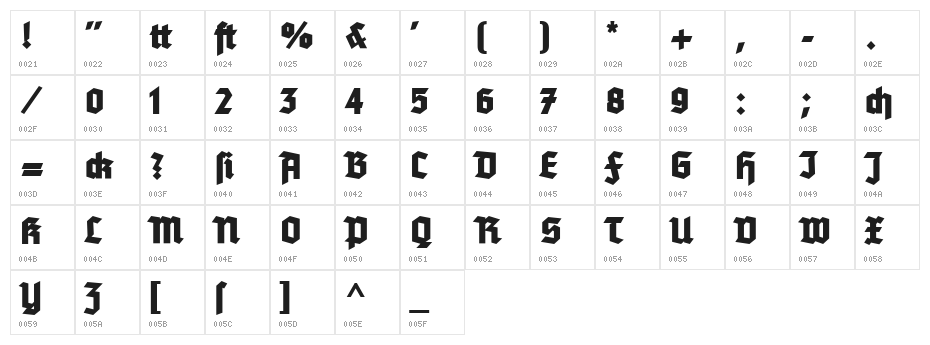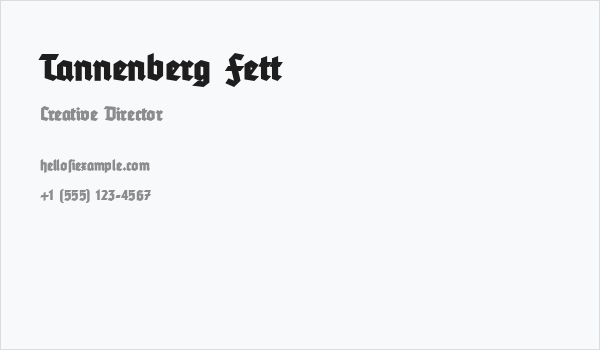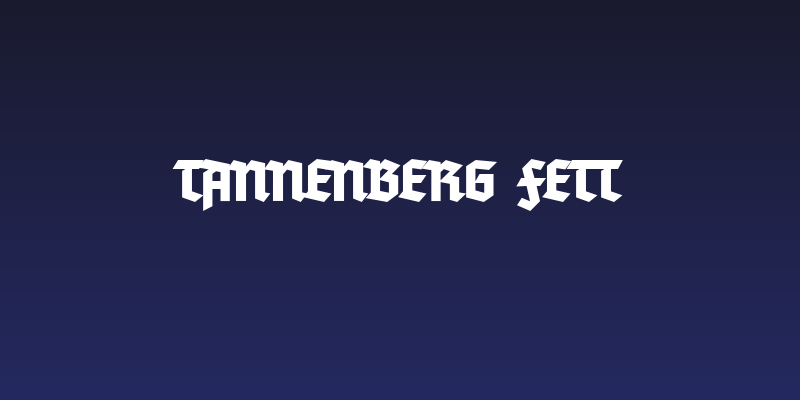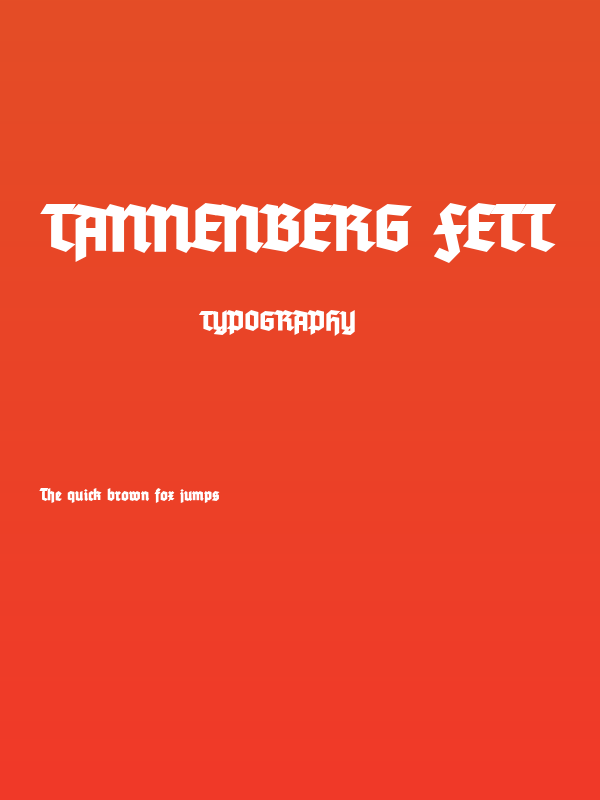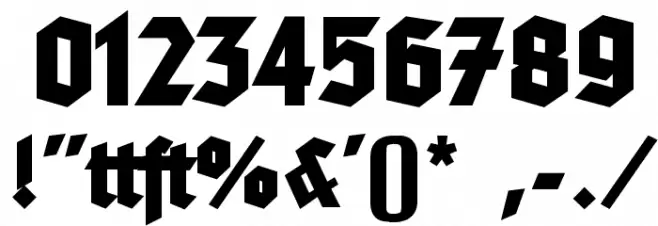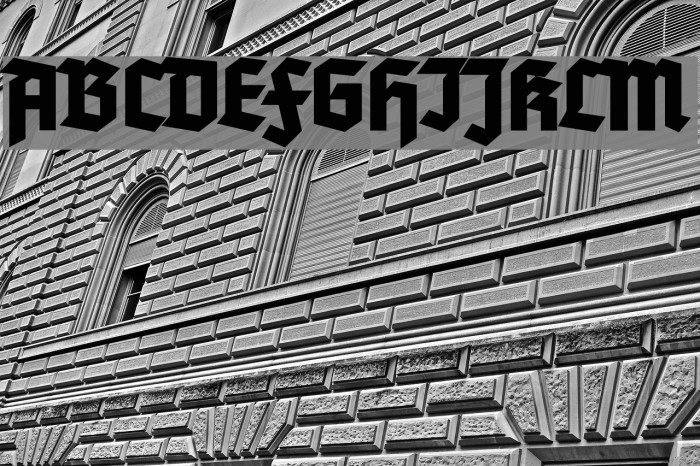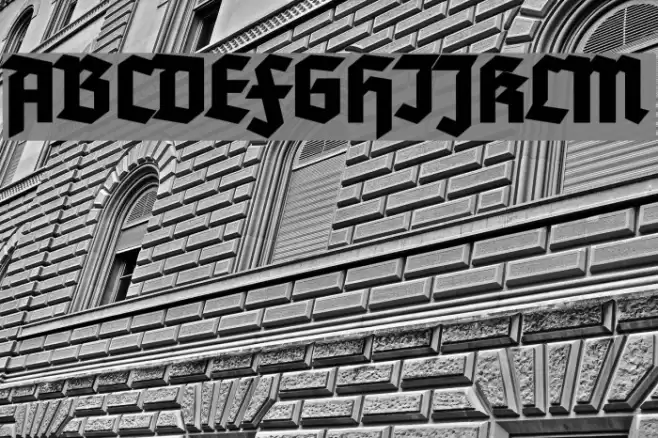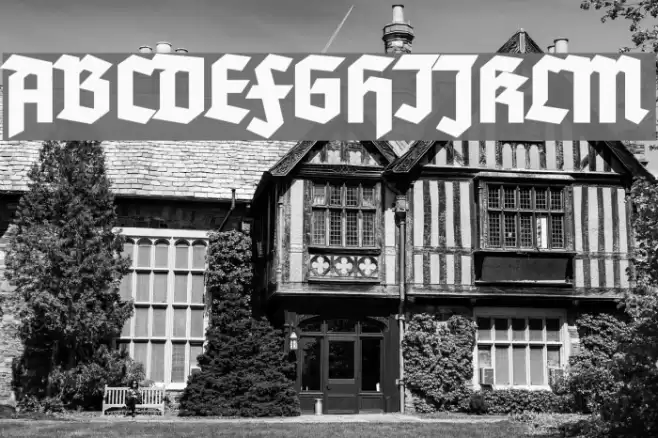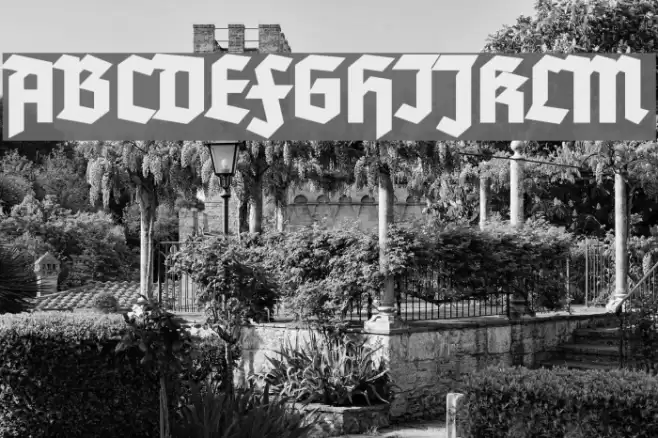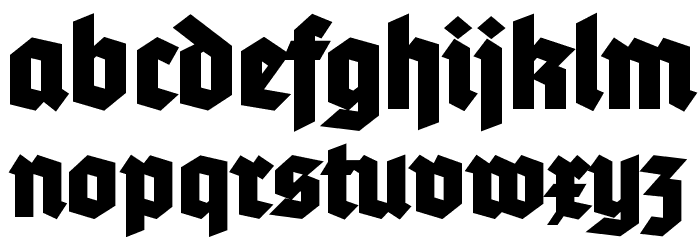
Tannenberg Fett Font
✎ Gothic
| Projetos propostos | Ideal for projects requiring a historical or gothic aesthetic, such as posters, book covers, or branding for vintage-themed products. |